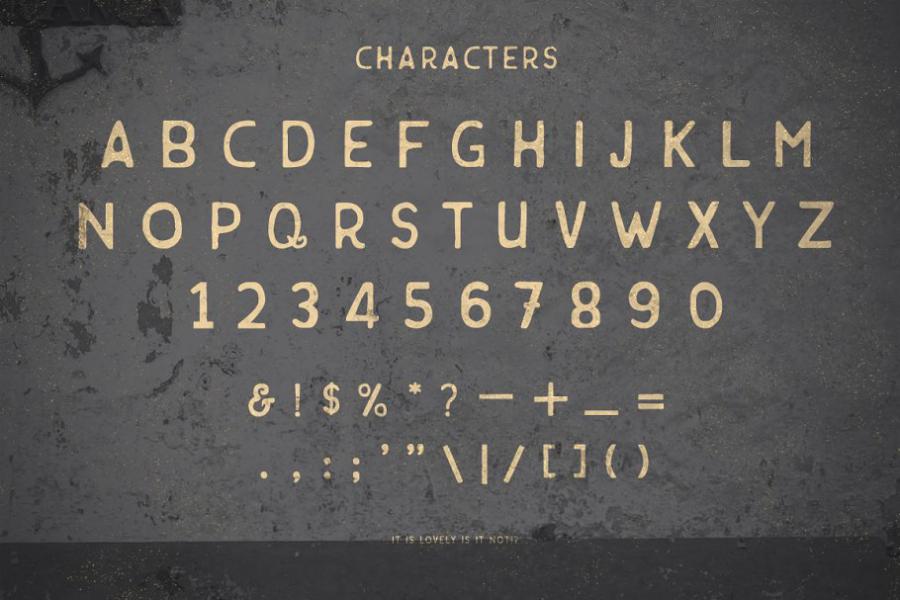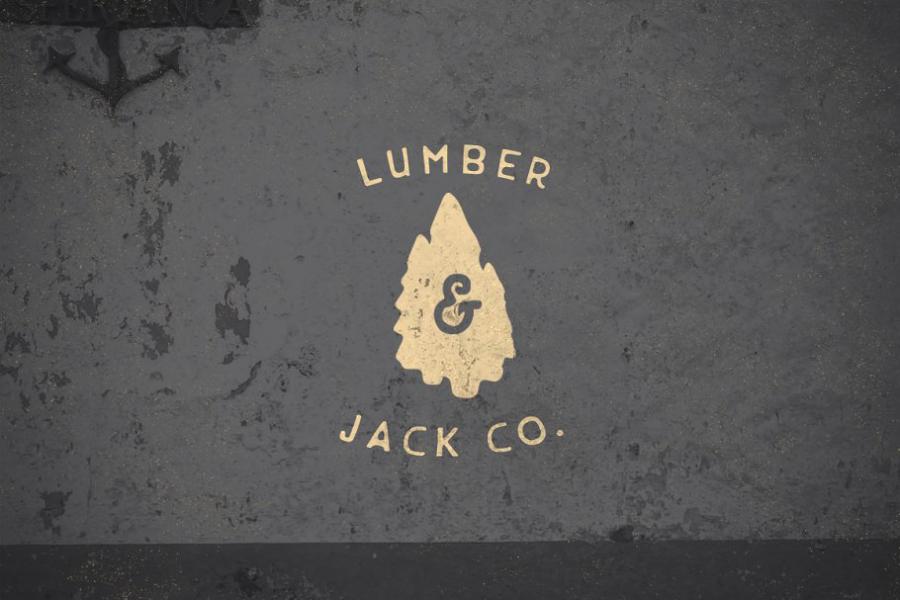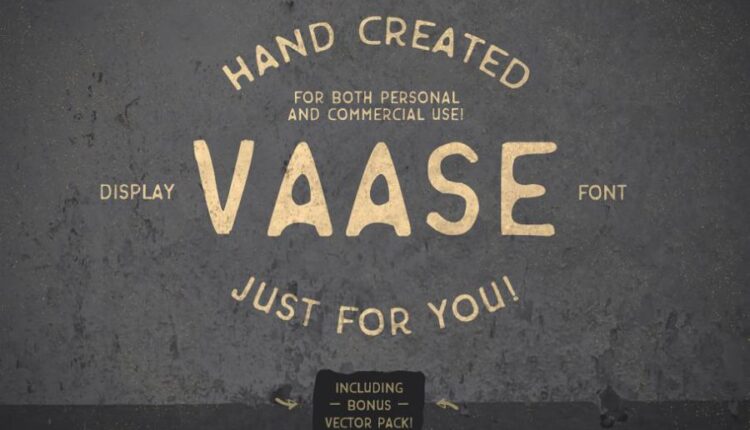
فونت انگلیسی نمایشی واس – Vaase Font + Bonus license
Vaase is a hand drawn bold display font available for both personal and commercial use.
This font is great for logo’s and wordmarks and partners well with script fonts to give your design the look and feel it needs!